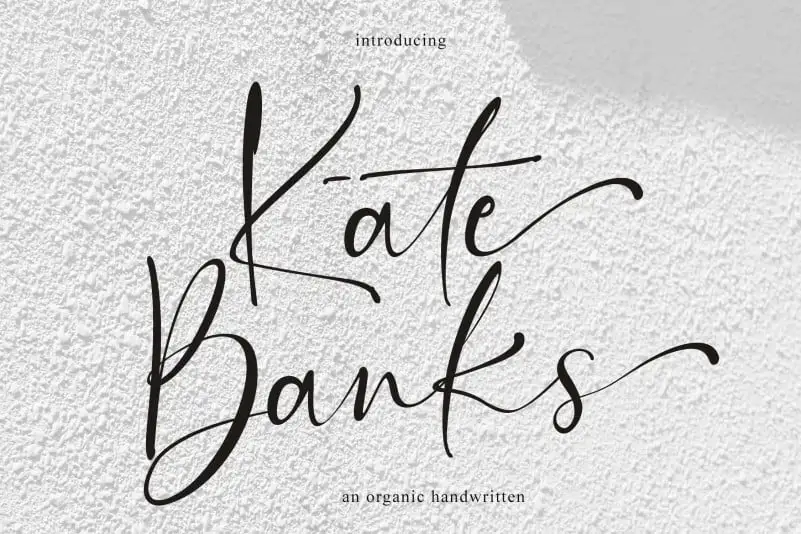
Kate Banks Calligraphy Font – Download Grátis
Introduzimos a Kate Banks Calligraphy Font – uma tipografia escrita à mão suave, elegante e fluente, criada pela Tikara. Esta tipografia é ideal para quem busca uma fonte que ofereça muitas opções de caracteres para criar designs únicos, sejam eles legíveis ou versáteis. Com 59 ligaturas ao seu dispor, esta extraordinária coleção mantém o estilo elegante e escrita à mão. Ela vai dar um toque perfeito aos seus projetos, seja em cartazes de eventos, anúncios ou qualquer tipo de design gráfico que você precise criar. Esta fonte irá lhe fornecer uma infinidade de opções para personalizar seu projeto, criando um look único e elegante.